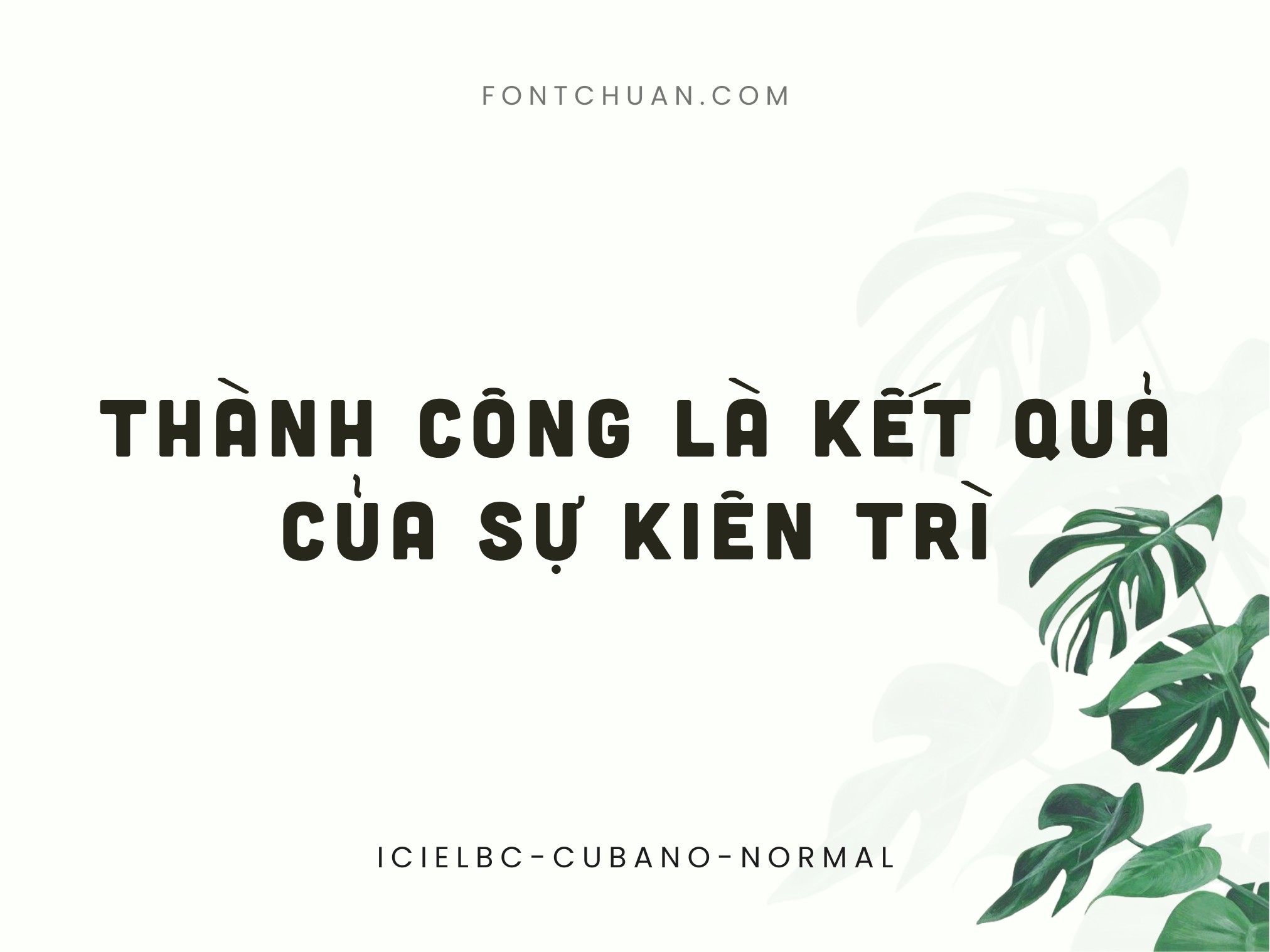
Font iCiel Bc Cubano Normal Việt Hóa
Tác giả Font: Chandler Van De Water
Việt hóa bởi: Iciel
BC Cubano Normal là một font chữ sans-serif đậm nét với thiết kế góc tròn, mang lại cảm giác hiện đại và thân thiện. Được thiết kế bởi Chandler Van De Water, font này nổi bật với các ký tự in hoa và đường nét rộng rãi, tạo sự thu hút mạnh mẽ trong các thiết kế. Để hỗ trợ cộng đồng thiết kế Việt Nam, Iciel đã Việt hóa font BC Cubano Normal, giúp font này hỗ trợ đầy đủ tiếng Việt cùng hơn 200 ngôn ngữ khác. Phiên bản BC Cubano Normal Việt hóa đã được thành viên Font Chuẩn sưu tầm và đăng tải, mang đến sự lựa chọn đa dạng cho các nhà thiết kế.
Về đặc điểm thiết kế, BC Cubano Normal sở hữu các ký tự in hoa với nét chữ đậm và góc bo tròn, tạo nên sự cân đối giữa tính mạnh mẽ và sự mềm mại. Font này rất phù hợp cho các thiết kế như tiêu đề, poster, logo, bao bì sản phẩm và các dự án cần sự nổi bật. Ngoài ra, BC Cubano Normal cũng là lựa chọn lý tưởng cho các ngành nghề như quảng cáo, bất động sản, giáo dục và công nghệ, mang lại phong cách chuyên nghiệp và hiện đại. Font này cũng thích hợp để sử dụng trong các sự kiện như lễ hội, sinh nhật và các dịp đặc biệt khác.